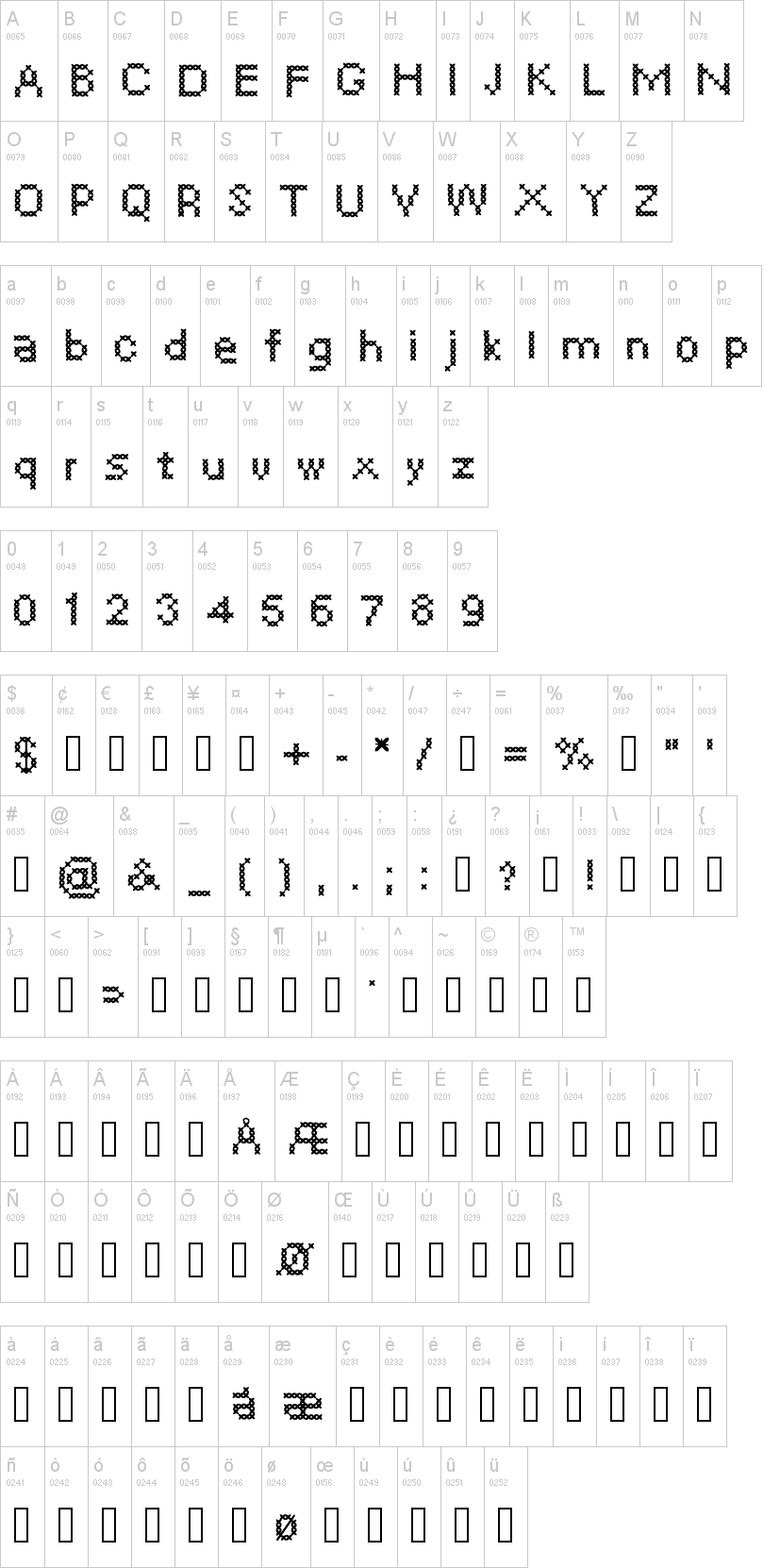
Cross Sew 字体是一种基于手工刺绣字体设计的字体,其特点是有一种手工艺感和独特的风格。该字体的设计灵感来自于针线和刺绣,因此其外观类似于用线缝制的字母。 Cross Sew 字体的特点包括: 1. 带有明显的线条和线缝效果,突出了手工艺感。 2. 常见的字母形状比较简单,且大多采用直线和直角的形式。 3. 字体的整体感觉比较平稳和稳定,与手工刺绣的风格相符合。 4. Cross Sew 字体常用于与手工艺相关的设计领域,比如刺绣、手工艺品、手工制品等。 总的来说,Cross Sew 字体是一种非常有特色和独特的字体,适合用于一些与手工艺相关的设计领域。内容介绍
Cross Sew是一款非常不错的手写艺术字体,具有很好的视觉感,适合于文化类的宣传设计、商业类品牌的广告和产品包装设计以及个性化文字排版等较多场景。